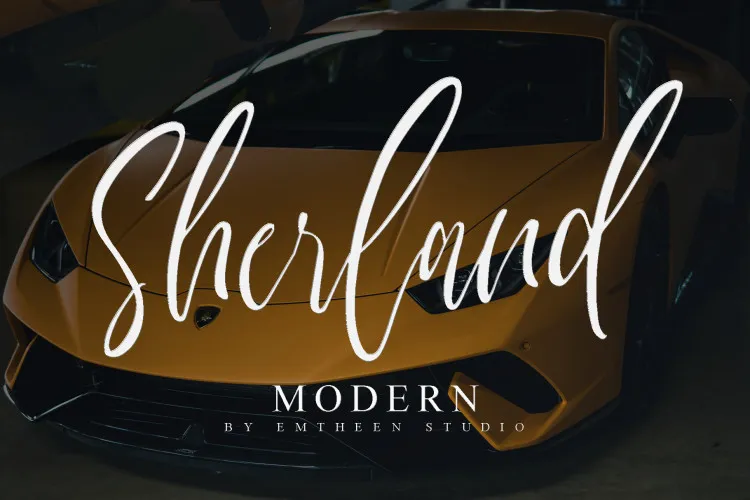
Sherland Script Font – Download Grátis
Descubra a Sherland Script Font, uma elegante escolha para quem busca dar um toque moderno aos seus projetos digitais. Esta fonte foi criada pelo designer f0rdesigner e é perfeitamente adaptada para aplicações onde você deseja se destacar. Com linhas finas e alturas de letras acentuadas em cada letra, ela proporciona um visual elegante e moderno que se destaca ao longo dos documentos e design gráfico. Ideal para uso em projetos relacionados à comunicação pessoal (como convites para casamentos ou cartões personalizados), identidade de marca, material de escritório e redes sociais. A Sherland Script Font é perfeita para quem quer dar um toque sofisticado a seus materiais de marketing digital, sem deixar de lado o brilho pessoal que os convites de casamento precisam. Uma fonte moderna que não apenas se adapta a suas necessidades de design, mas também encanta seu público final.